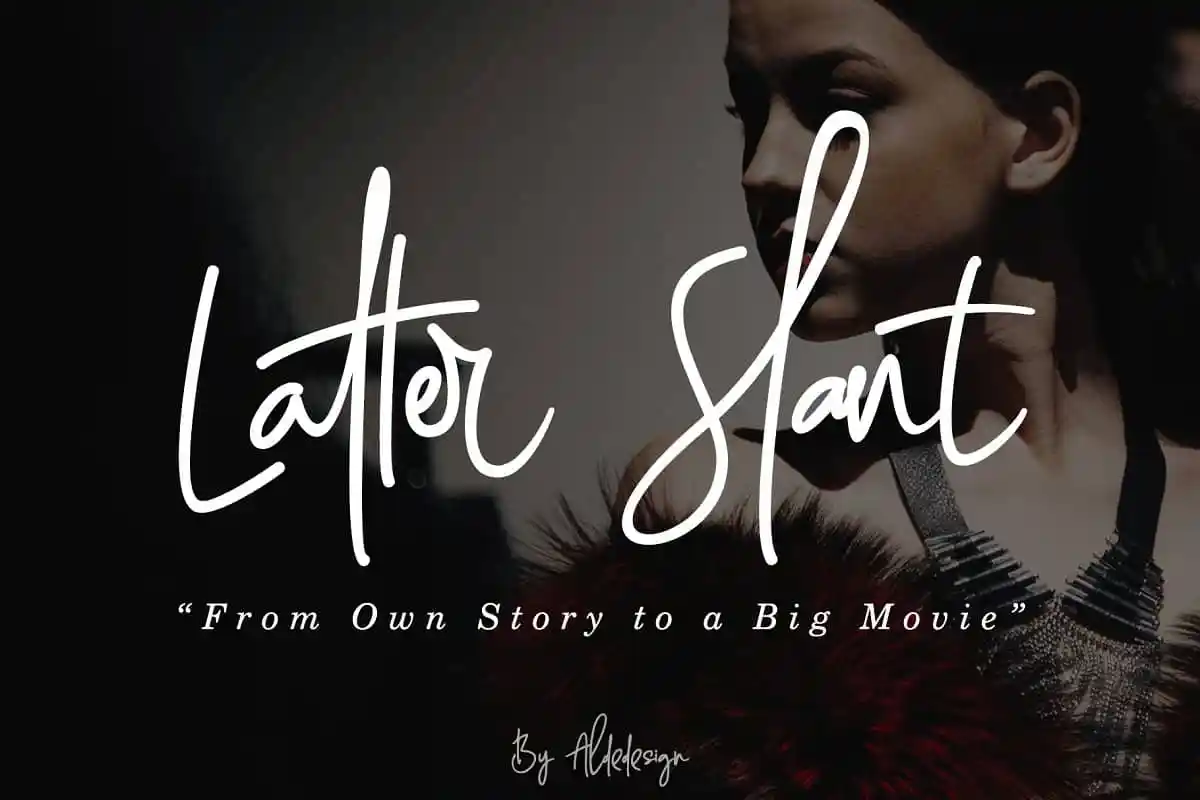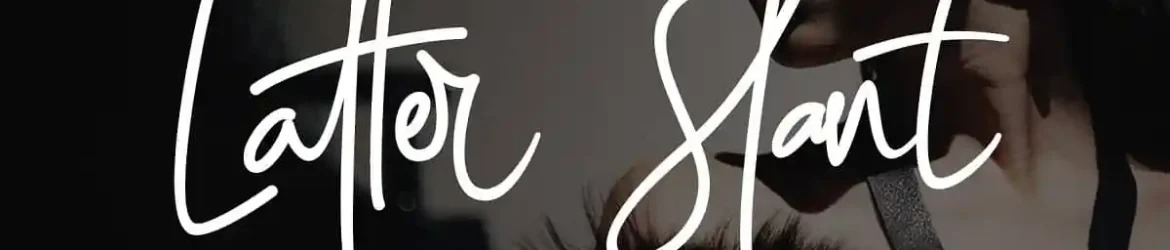
Latter Slant Signature Font – Download Grátis
Lembro a vocês sobre uma nova adição à nossa categoria de Fonts Script: Latter Slant Signature Font. Criada pelo designer Aldedesign, esta é uma fonte que oferece um toque de estilo e classe única, com seu aspecto elegante e envolvente. O Latter Slant Signature traz uma sensação natural que se reflete em suas ligaturas, tornando-o perfeito para diversos projetos gráficos. A sua tipografia é levemente curvada, oferecendo um toque distintivo que certamente manterá qualquer design atraente e sofisticado. Este fonte é especialmente adequado para aplicar como marca d’água em projetos de branding, design editorial, casamentos, fotografia, assinaturas pessoais ou profissionais, logotipos, capas de álbum, cartões de visita, citações e mais. Com sua beleza clássica e leitura fluida, a Latter Slant é definitivamente um recurso que todos os designers deveriam ter em seu arsenal.